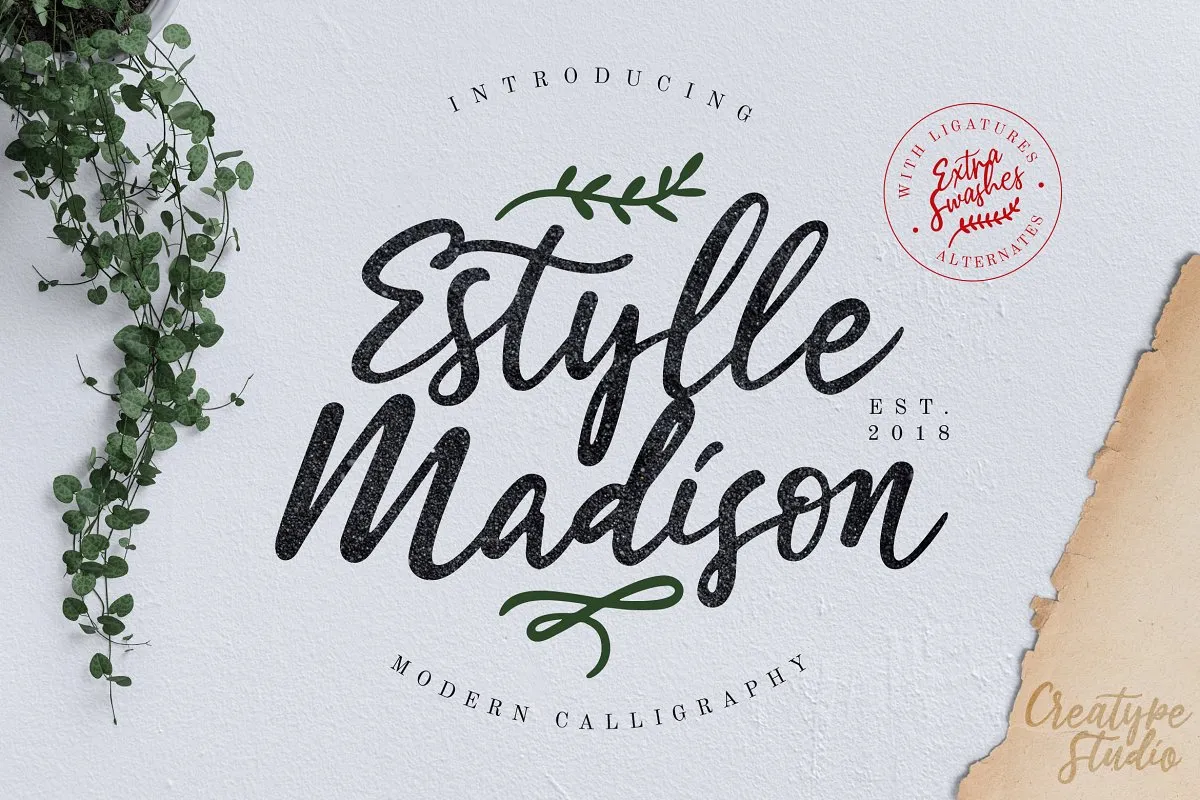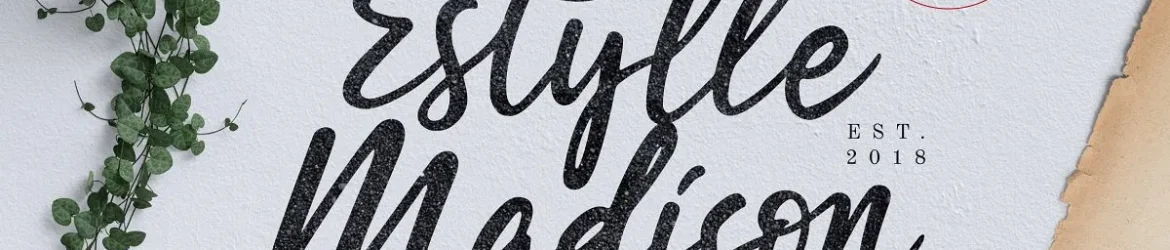
Estylle Madison Script Font – Download Grátis
Estylle Madison Script é uma fonte script que se destaca por sua elegância natural e moderna. Inspirada nas antigas propagandas, esta fonte foi elaborada com mão na arte de uma chamada artística. A Estylle Madison tem um tom sofisticado e refinado, convidativo para quem busca personalidade em seus projetos gráficos. Ideal para inúmeras aplicações, a Estylle Madison é perfeita tanto para logomarcas e identificações de marca como para cartões de convite, materiais de correspondência, designs de casamentos, posts nas redes sociais, anúncios, embalagens de produtos, projetos de produto, selos, fotografia ou até mesmo para marcas especiais. Seja qual seja o seu projeto, esta fonte tem a capacidade única de dar um toque elegante e autêntico ao conteúdo. A Estylle Madison é uma opção fantástica para quem busca adicionar charme e personalidade à sua identidade visual, seja em um projeto pessoal ou profissional. Com o seu movimento natural e fluido na escrita, a fonte traz uma sensação de sofisticação que certamente deixará sua marca imortável.